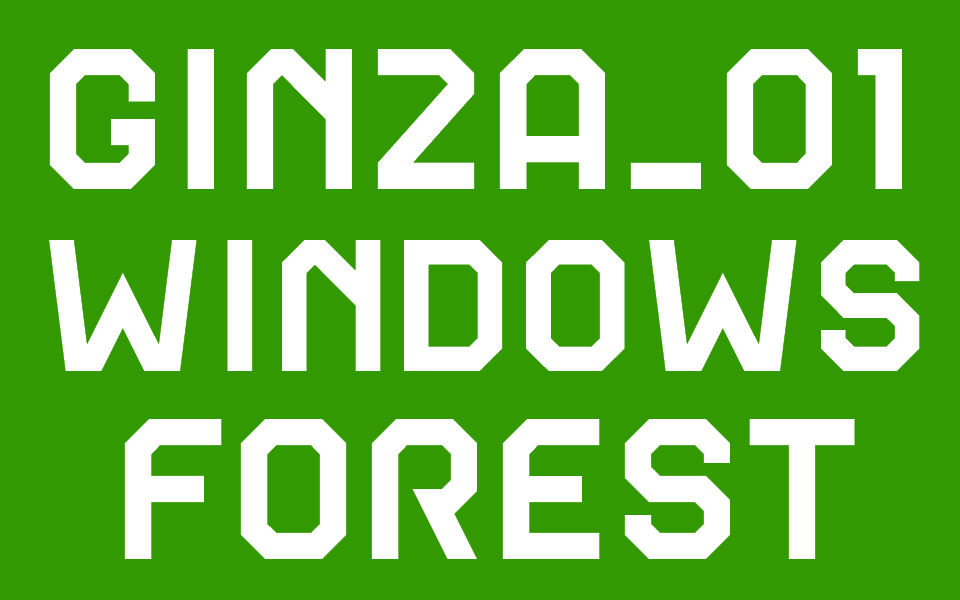
地下鉄車両“銀座線01系”の引退を記念する非公式英字フォント「GINZA_01」
レトロフューチャーな雰囲気を醸し出す直線的なデザイン
「GINZA_01」は、1984年に営業運転が開始された“銀座線01系”の車両デザインを文字化した非公式フォント。大文字のアルファベットと数字、一部の記号を収録している。
東京メトロ銀座線の“01系”車両を特徴づける部位は、トンネルの形状に合わせて斜傾した屋根の両肩。「GINZA_01」もそのデザインを取り入れ、正面から見たときの“顔”を連想させる。
また、同車両の直線的なアルミ製ボディは30年以上が経過した今でも洗練された印象を受ける。そのレトロフューチャーな雰囲気は「GINZA_01」にも表れており、同時期に誕生したデロリアン社の自動車“DMC-12”に通じるものがあるだろうか。